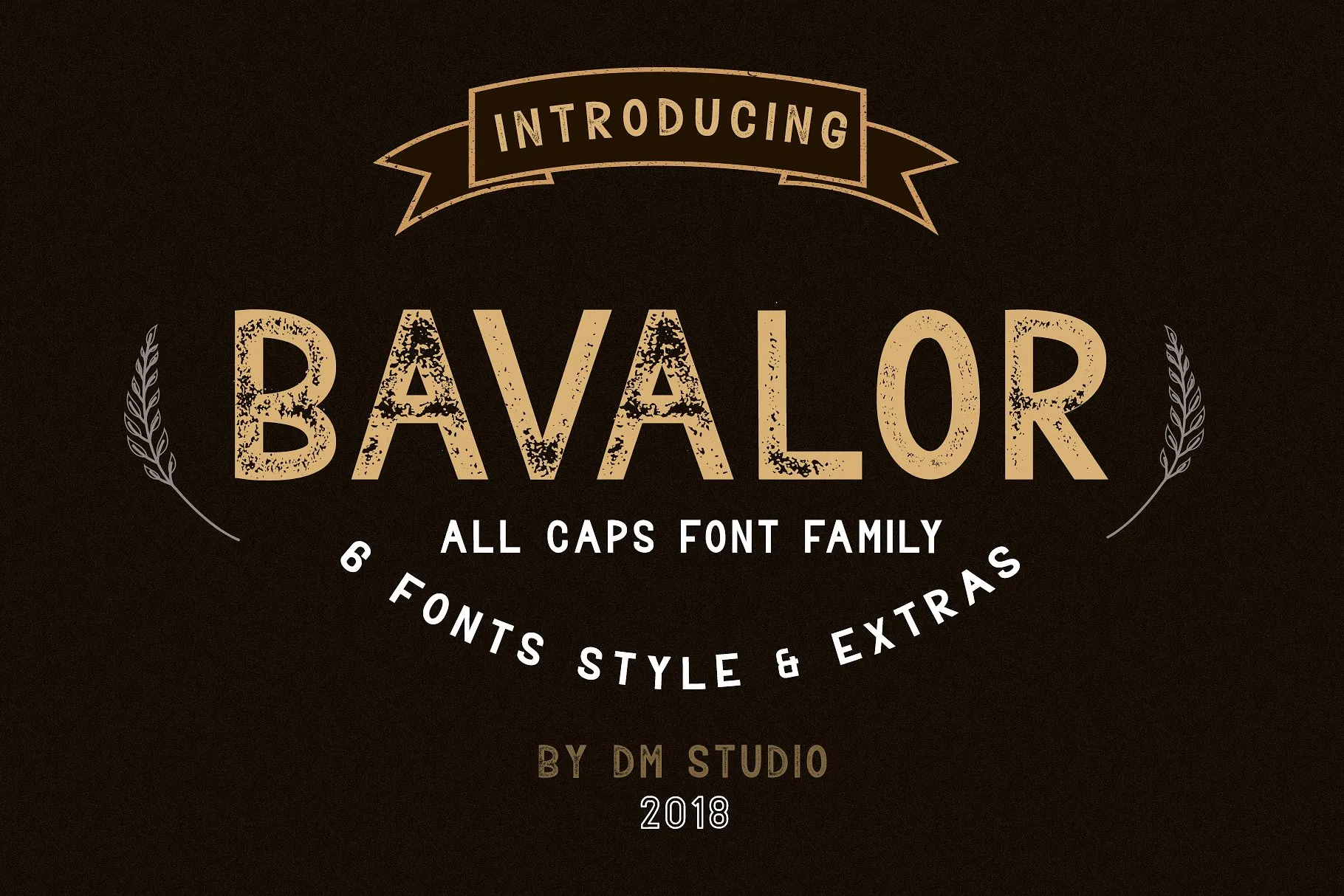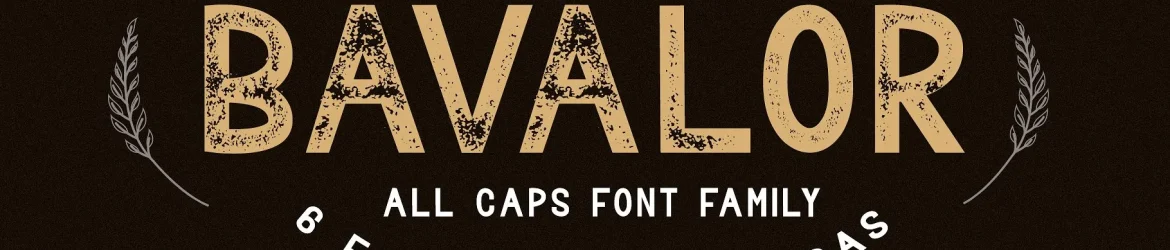
A Bavalor Typeface é uma família de fontes all caps que inclui 6 estilos diferentes e extras. A Dm.Studio concebeu essa famosa família de fontes. Composta por um sans serif, a Bavalor possui seis arquivos OTF e TTF, fornecendo versões normais, rústicas e com estilo itálico para você explorar. Esta familia única oferece muitas opções de personalização. Você pode usar as diferentes versões juntas ou optar por cada uma individualmente. Ela é perfeita para qualquer projeto, seja ele gráfico digital, jornalismo, design editorial ou até mesmo em arquitetura e urbanismo. Com uma aparência dinâmica e moderna, a Bavalor se destaca entre as fontes all caps existentes por sua grande variedade de estilos e graça visual. Ela é um excelente complemento para qualquer projeto que você esteja desenvolvendo, adicionando um toque poderoso sem dúvida ao seu design.